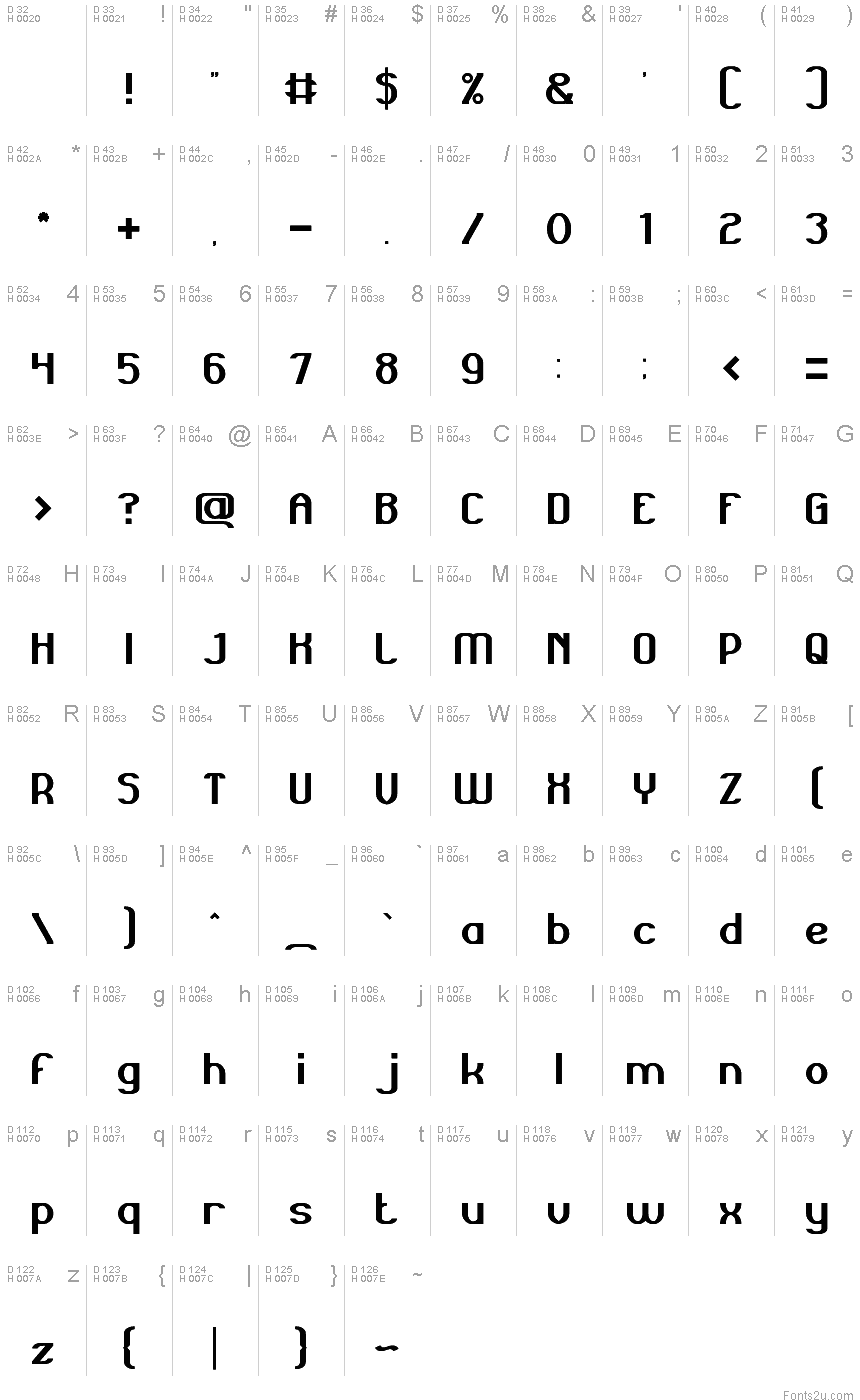
Grand Prix od Weknow to darmowy, utrzymany w stylu retro font typu display, który zamienia każde słowo w wyrazisty emblemat. Wysokie, wąskie litery z zaokrąglonymi rogami i masywnymi pionowymi liniami tworzą szybki, mechaniczny rytm, a niebanalne otwarte krzywizny sprawiają, że font nie jest ani chłodny, ani pospolity. Całość przywodzi na myśl plakaty wyścigowe w stylu vintage oraz napisy na deskach rozdzielczych – jest odważnie, z pazurem i odrobiną nostalgii.
Grand Prix sprawia, że nagłówki zyskują czystą, skondensowaną formę, oszczędzając miejsce bez utraty siły przebicia. Ten darmowy font świetnie sprawdzi się na plakatach, w brandingu sportowym, przy projektach związanych z wyścigami, na grafikach odzieżowych, tytułach gier czy przyciągających wzrok banerach w mediach społecznościowych. Spróbuj połączyć go z prostym geometrycznym bezszeryfowcem w mniejszym tekście, a w większych rozmiarach pozwól Grand Prix grać pierwsze skrzypce, aby uzyskać maksymalny efekt.